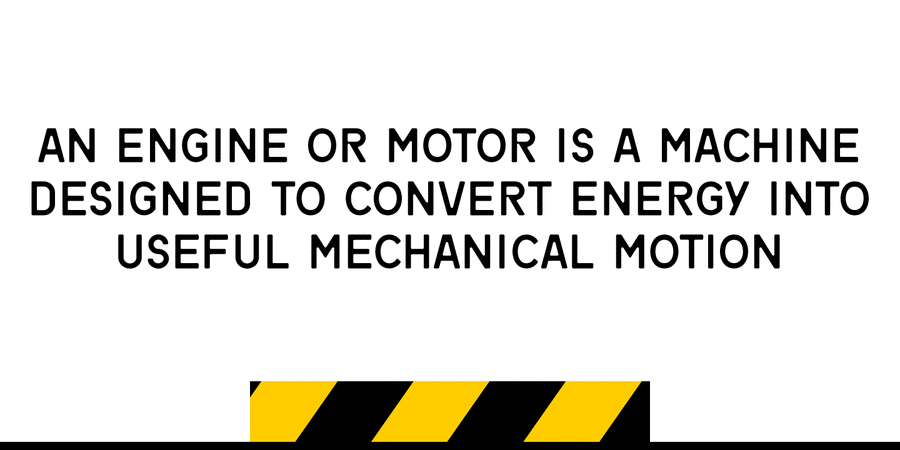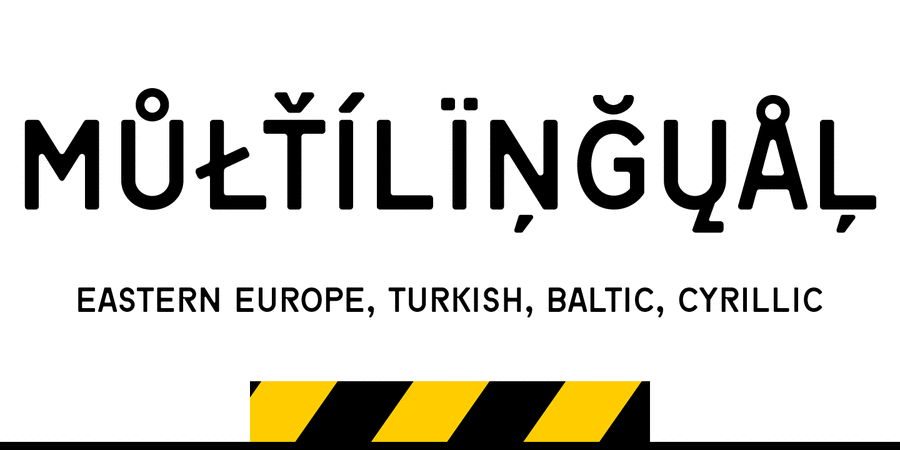
About Motor 4FМотор — акцидентный щрифт, сделан по мотивам букв автомобильных номерных знаков, принятых в России. Разработан Сергеем Ткаченко в 2014 году.
accurate, flat, convincing, rectangular, stable, static, simple, neutral, straight, modern, globalized, globalistic, monotone, logical, pragmatic, practical, solid, laconic, available, serious, iron, steel, reliable, self-assured, strong, automatic, artificial, cold, machine, engineering, industrial, technogenic, military, army, standard, urban, rude, workman, indifferent, motivating, railway, important, heavy, severe
industry, equipment, machine tool, code, packing, power station, energy industry, army, weapons, mechanical engineering, factory, scheme, constructor, engineer, automation, car, motor, ГОСТ, press, city, navigation, science, mine, miner, helmet, uniform, railway carriage, aviation, aircraft, airsoft, construction, building, technology, railway, fuel, workman, repairs, show, TV, truck, SUV, footwear, brick, trucker, steel-maker, engine, Delivery, oil Typeface associated with age: